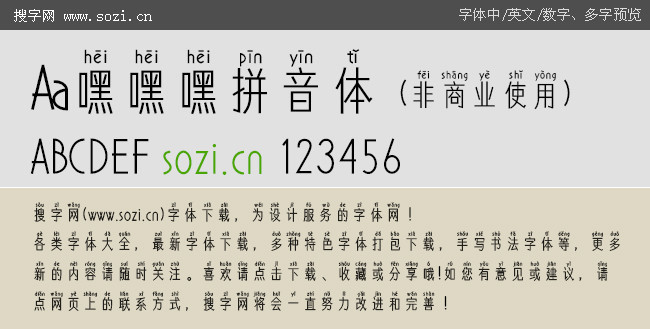
Aa嘿嘿嘿拼音體
搜字網(wǎng)給大家提供一款A(yù)a嘿嘿嘿拼音體(非商業(yè)使用)中文字體下載,該字體筆劃線條纖細(xì),并帶有拼音,字形整體效果非常的出眾。適合書裝設(shè)計(jì)、包裝設(shè)計(jì)、海報(bào)設(shè)計(jì)等應(yīng)用(此字體為個(gè)人非商用版,商用可以聯(lián)系QQ:1006760504)。